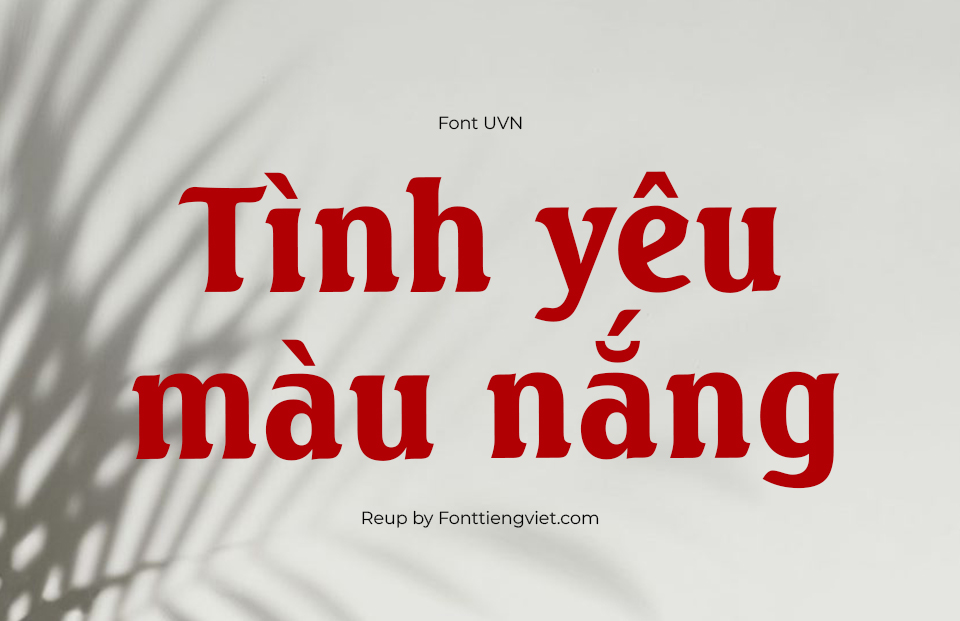
Font Việt Hóa UVN Chim Bien Nang
Giới thiệu về Font Việt Hóa UVN Chim Bien Nang
Trong thế giới thiết kế đồ họa tại Việt Nam, việc lựa chọn một bộ Font Miễn Phí chất lượng là yếu tố quyết định sự thành công của sản phẩm. Font Việt Hóa UVN Chim Bien Nang nổi lên như một lựa chọn hàng đầu nhờ phong cách chữ đậm, rõ ràng và đầy chuyên nghiệp. Đây là bộ phông chữ nằm trong dự án UVN nổi tiếng, được tối ưu hóa hoàn toàn cho bảng mã Unicode, giúp người dùng dễ dàng gõ tiếng Việt mà không lo lỗi font hay thiếu dấu. Với đường nét chắc chắn, kiểu chữ này mang lại cảm giác tin cậy và trang trọng cho mọi văn bản.
Đặc điểm nổi bật của Font Việt Hóa UVN Chim Bien Nang
Phong cách thiết kế và ứng dụng
Font Việt Hóa UVN Chim Bien Nang sở hữu độ dày ấn tượng, rất phù hợp để làm tiêu đề bài giảng, băng rôn khẩu hiệu hoặc các bảng thông báo trong nhà trường. Sự cân đối giữa các nét chữ giúp người xem dễ dàng tiếp nhận thông tin từ khoảng cách xa. Các giáo viên và học sinh có thể sử dụng bộ font này để trình bày bài thuyết trình PowerPoint thêm phần sinh động và lôi cuốn.
Khả năng tương thích linh hoạt
Kết luận về bộ font chữ ấn tượng